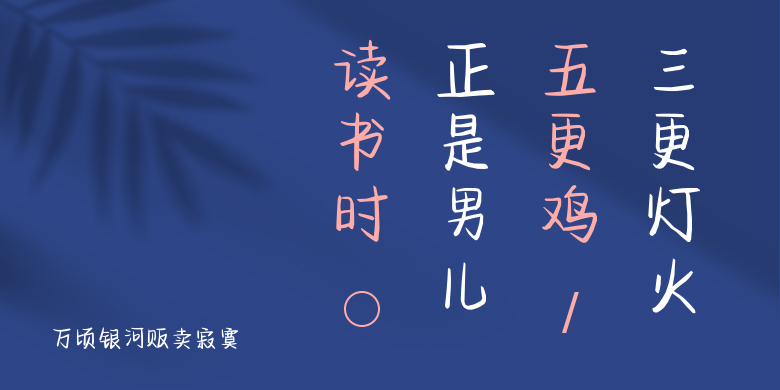
万顷银河贩卖寂寞
万顷银河贩卖寂寞,这款字体结构工整、笔画清晰,兼顾美观与易读性,适用于标题、正文、海报、包装、LOGO 等多种场景。字形优雅稳定,风格百搭耐看,适配日常排版与创意设计,让文字呈现更舒适、更具质感。万顷银河贩卖寂寞一笔一画,皆是细节,以均衡的比例、流畅的线条打造舒适视觉体验,字形端正大气,风格简约现代。无论是商业设计、品牌宣传还是日常排版,都能轻松驾驭,让文字更有格调与力量。万顷银河贩卖寂寞字体下载。